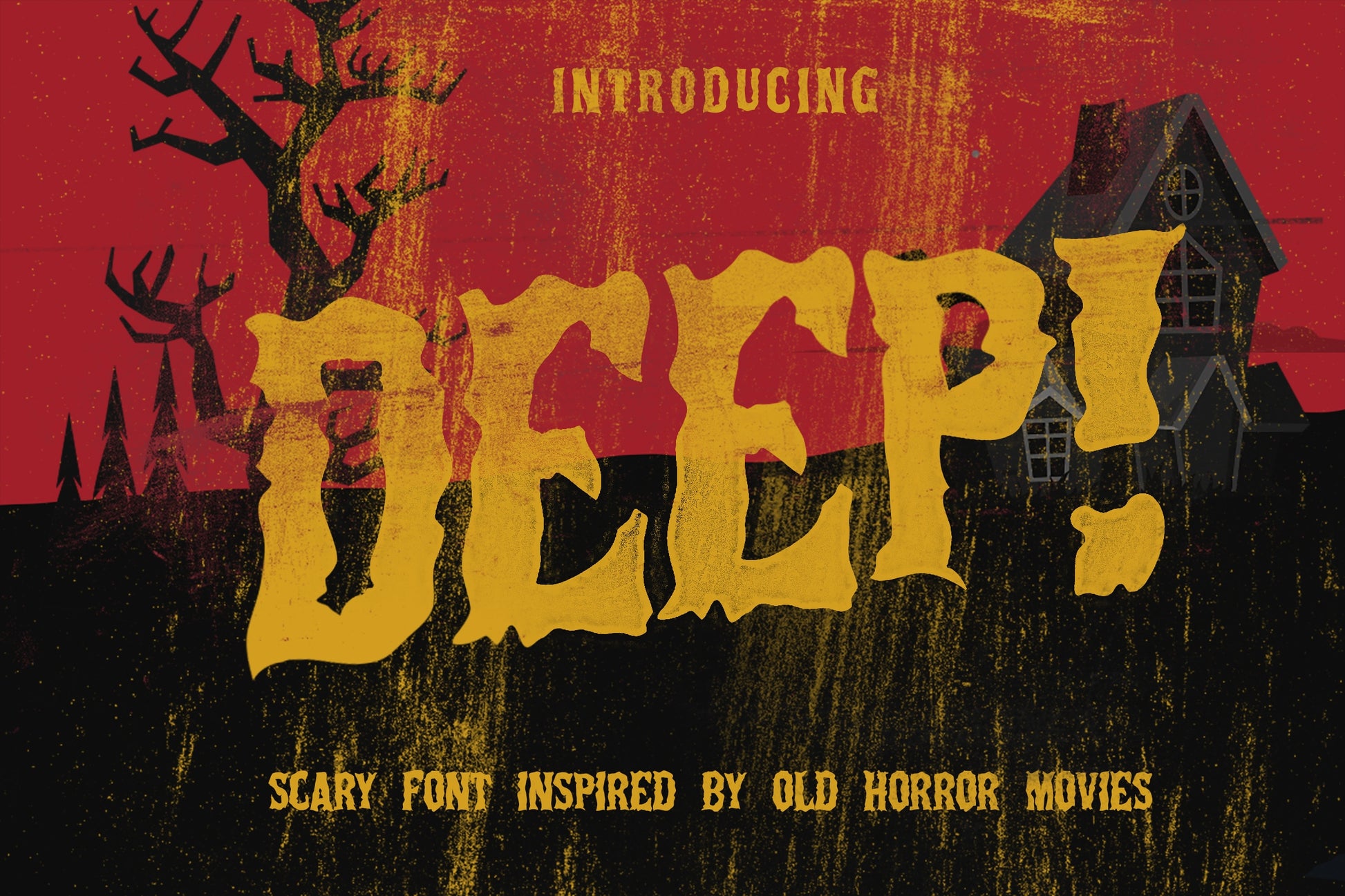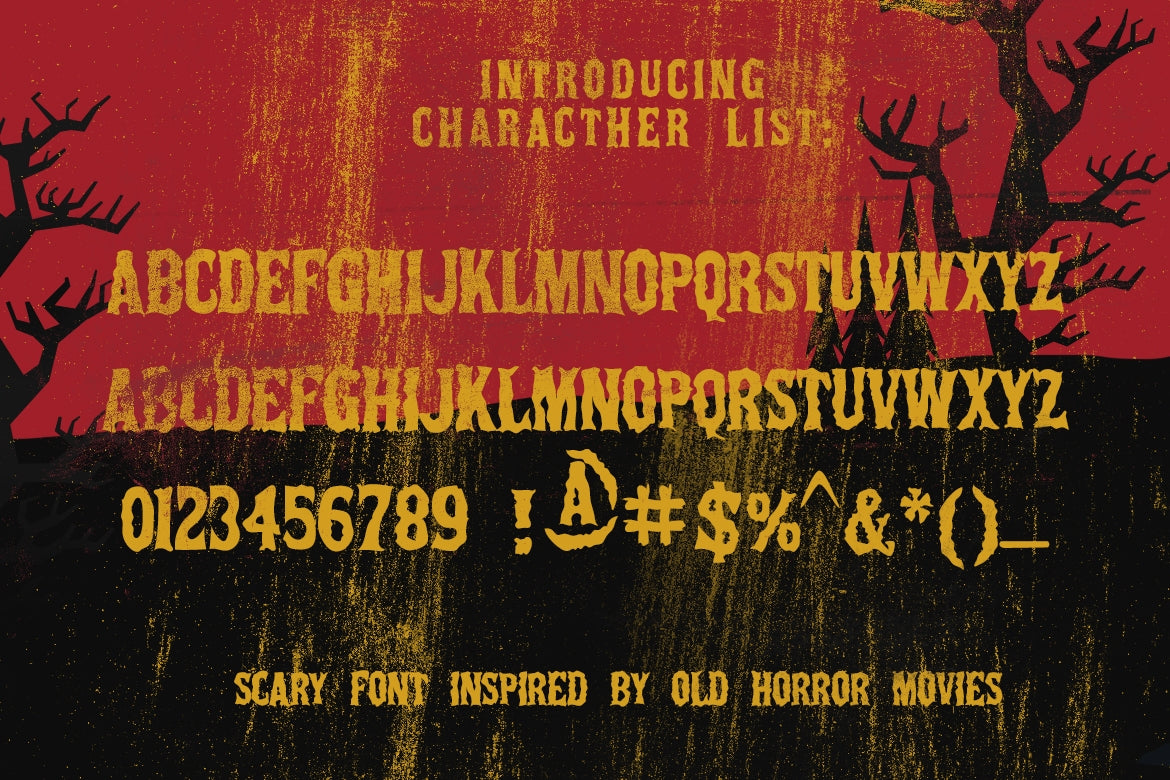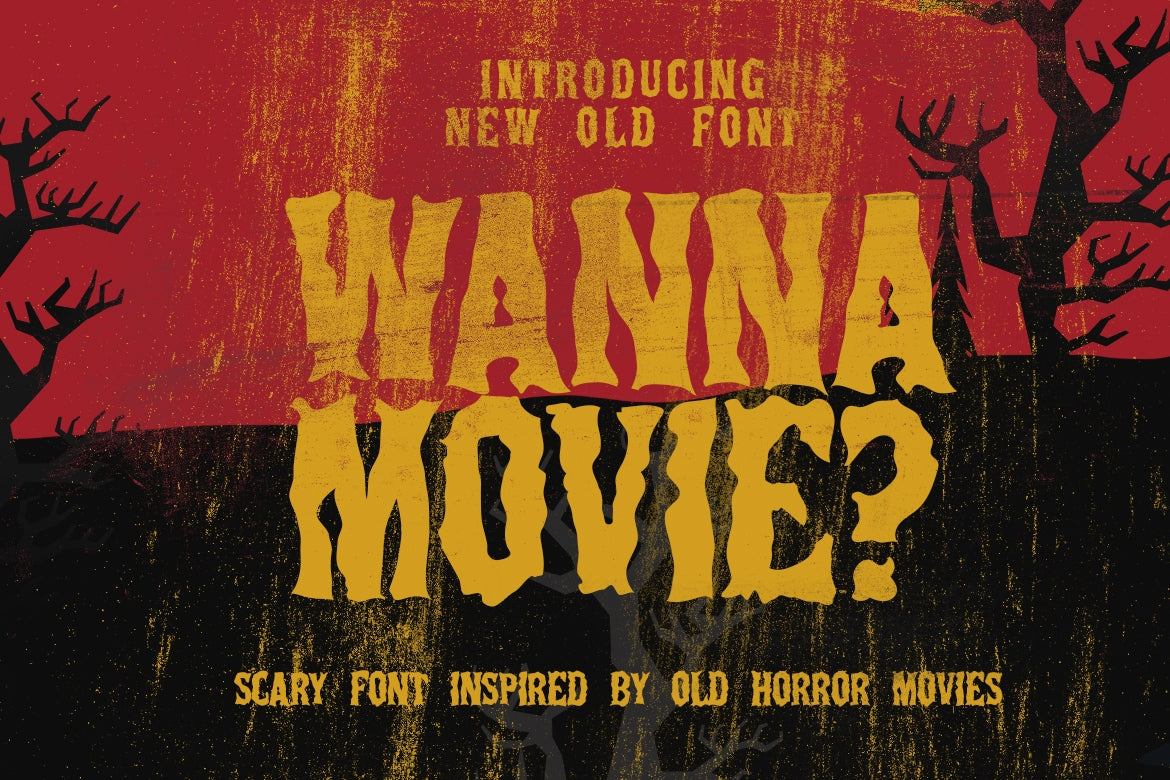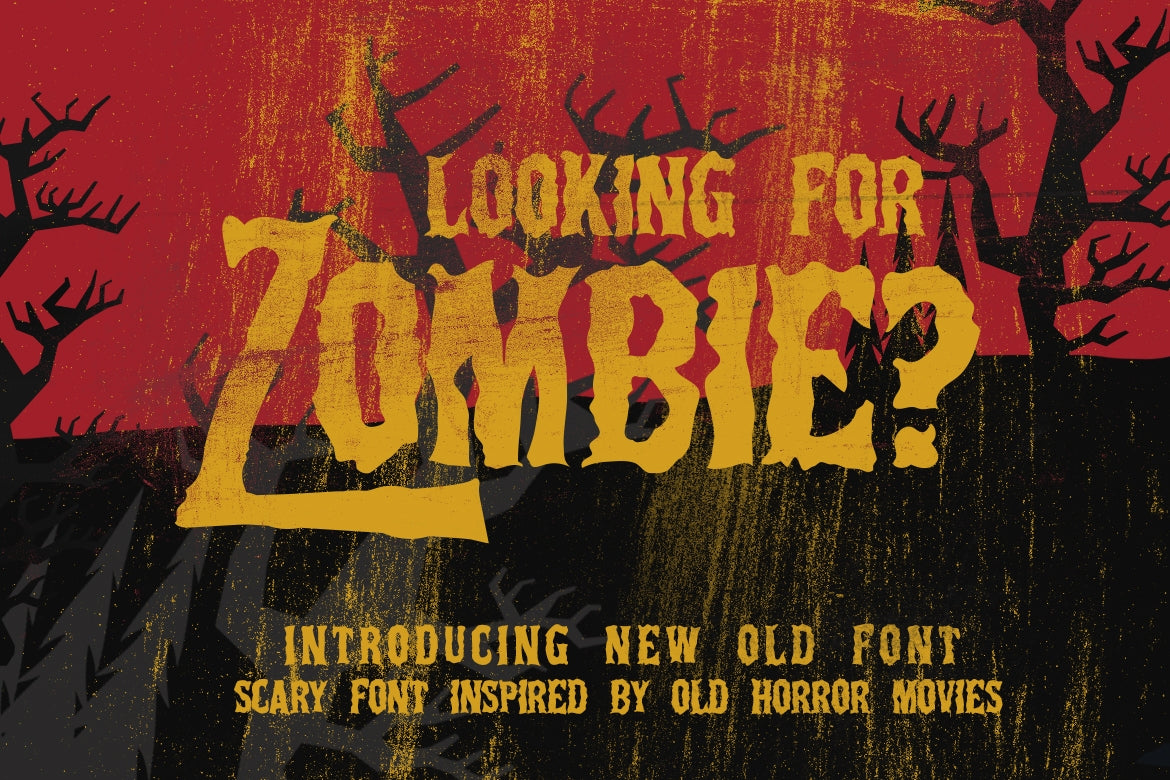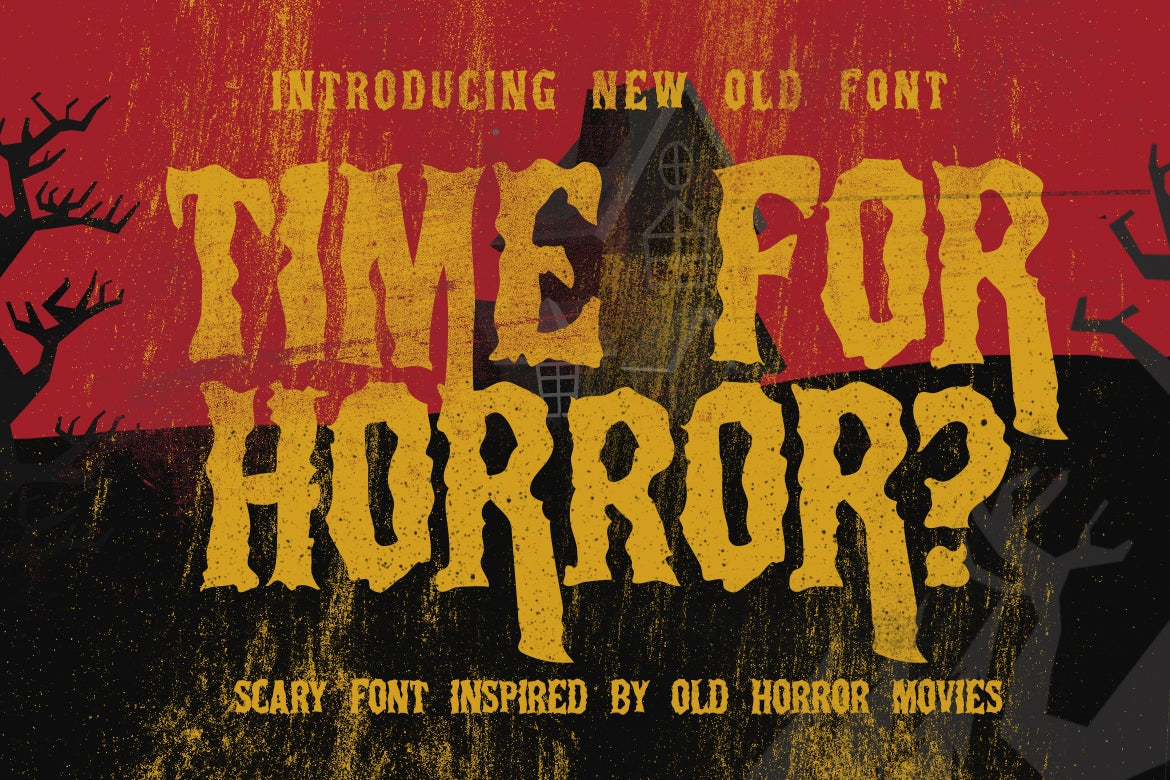
Fuente Deep Horror
Fuente Deep Horror, una fuente aterradora inspirada en películas de terror antiguas. Disponible en versiones NORMAL y INTEGRAL.
Adecuado para diseño, diseño de elementos, bodas, eventos, camisetas, logotipos, insignias, pegatinas y trabajos increíbles sobre el verano.
Ideal para mensajes llamativos. Hecho con marcador plano, añadiendo movimientos realistas. Ideal para logotipos, etiquetas de nombre, citas manuscritas, empaques de productos, artículos promocionales, redes sociales y tarjetas de felicitación. También es ideal para crear diseños de camisetas y otras prendas de vestir.
Además, la combinación y el uso de diferentes letras y ligaduras te da la oportunidad de divertirte y al mismo tiempo crear tu propio estilo único.
• Esta fuente incluye diacríticos latinos básicos.
Las fuentes incluyen soporte multilingüe para: ä ö ü Ä Ö Ü ß ¿ ¡